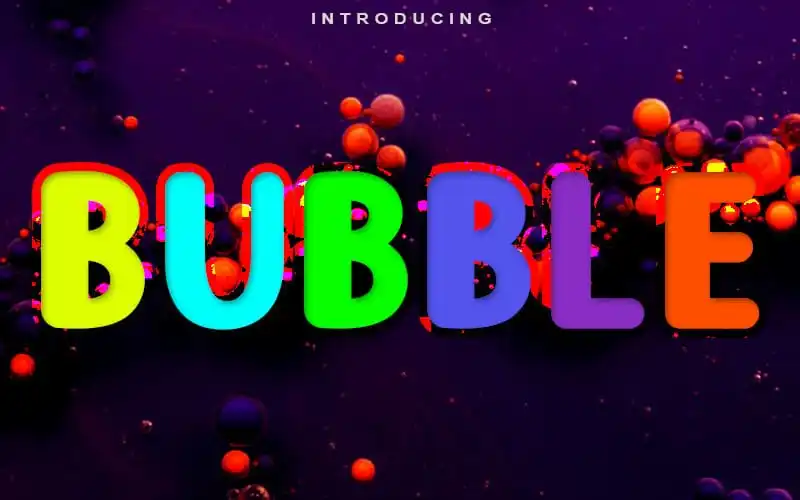
Bubble Display Font é uma fonte sans-serif que mantém sua elegância tipográfica clássica ao mesmo tempo em que se sente contemporânea e atual. Esta versatilidade a torna ideal para qualquer criatividade, seja ela em letras de cartão ou títulos de papelarias. Através do uso desta fonte, você pode explorar uma variedade de ideias únicas, perfeita tanto para criar apelativos postais quanto para dar um toque único a sua marca. Ideal para profissionais que buscam uma aparência sofisticada e atualizada em seus projetos, Bubble Display Font é a escolha perfeita para designers que querem agregar um toque especial ao seu design.